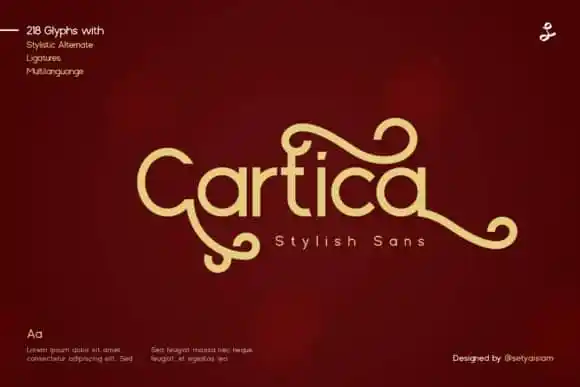
Cartica Sans Serif Font – Download Grátis
A Cartica Sans Serif é uma fonte de tipo aberto com aparência vintage, perfeita para projetos futuros. Seu designer, setyaisiam, criou esta fonte minimal e limpa que se adapta facilmente a um enorme número de propostas gráficas. Adicione-a à sua imaginação criativa e veja como ela destaca seus trabalhos. Uma das suas características mais interessantes é o seu look retro enquanto mantém uma aparência moderna e clara, tornando-se ideal para uma variedade impressionante de aplicações gráficas. Seja você um designer web ou impressão, publicidade ou marketing digital, a Cartica Sans Serif pode se adaptar perfeitamente ao seu trabalho. Com sua simplicidade e destreza na composição de fontes, esta é uma opção perfeita para aqueles que buscam uma fonte moderna com um toque vintage. Essa combinação de estilos torna a Cartica Sans Serif uma escolha excelente para designers que querem incorporar elementos nostálgicos em seus projetos sem comprometer a clareza e eficácia do design.